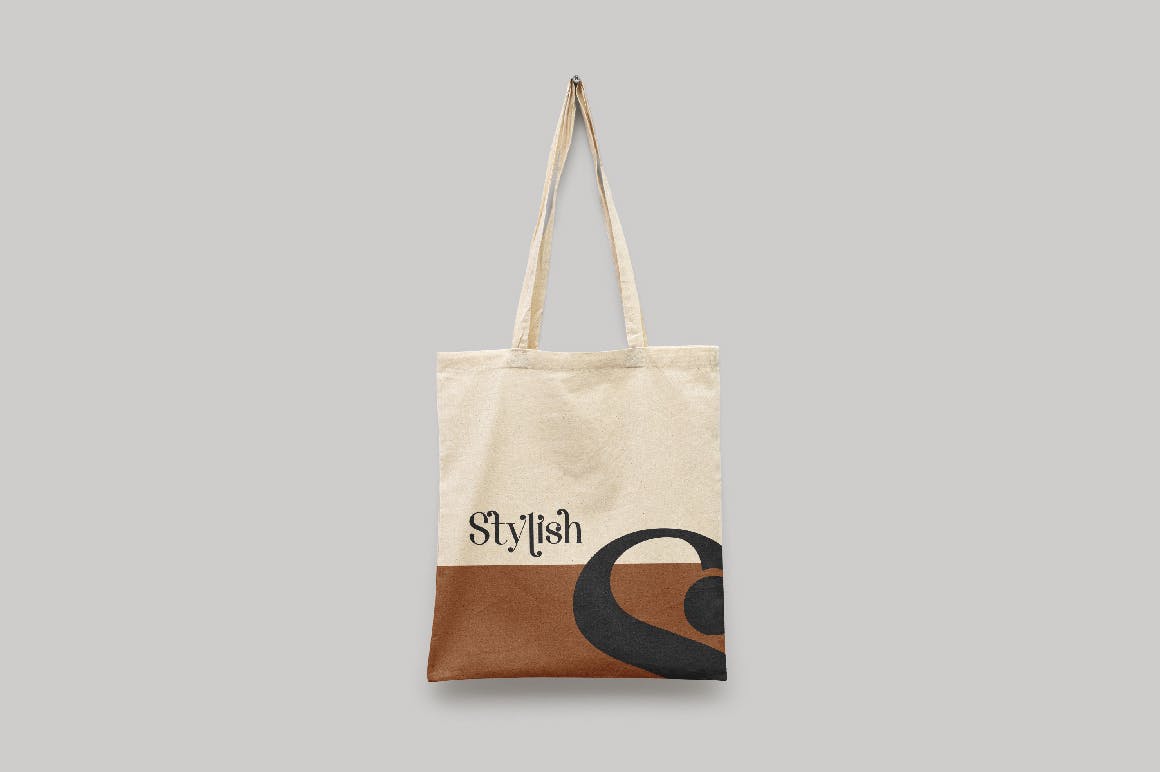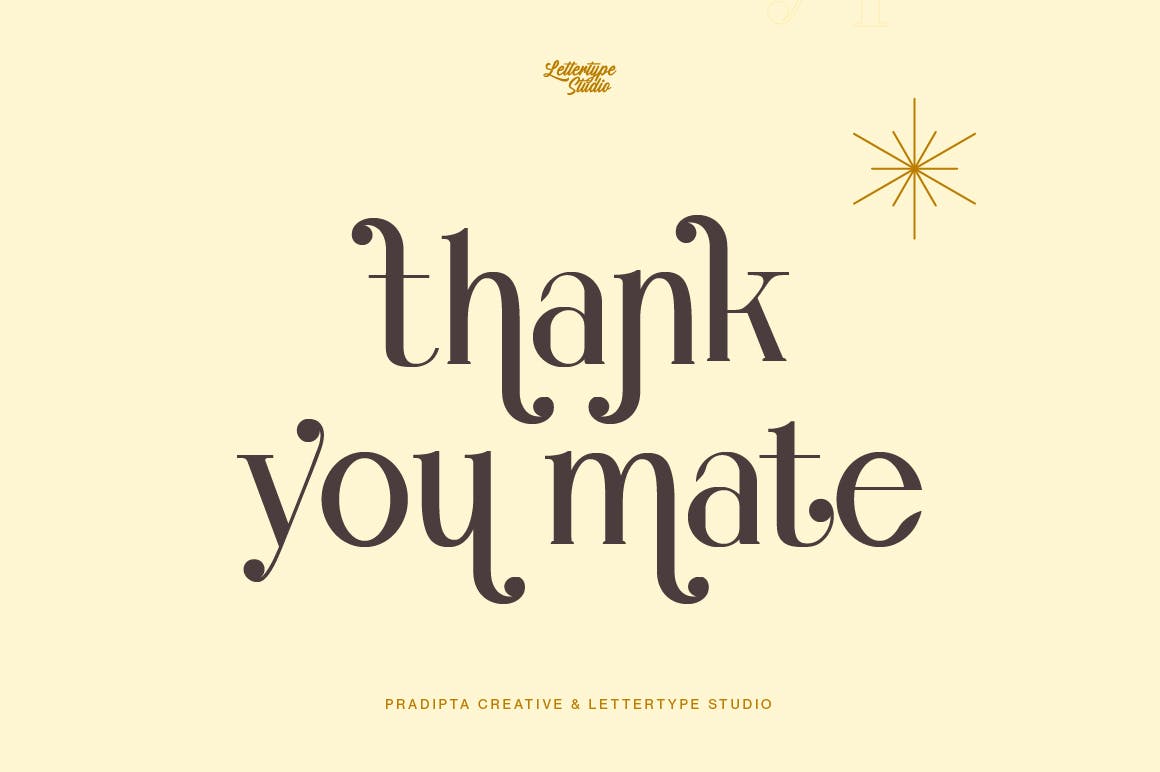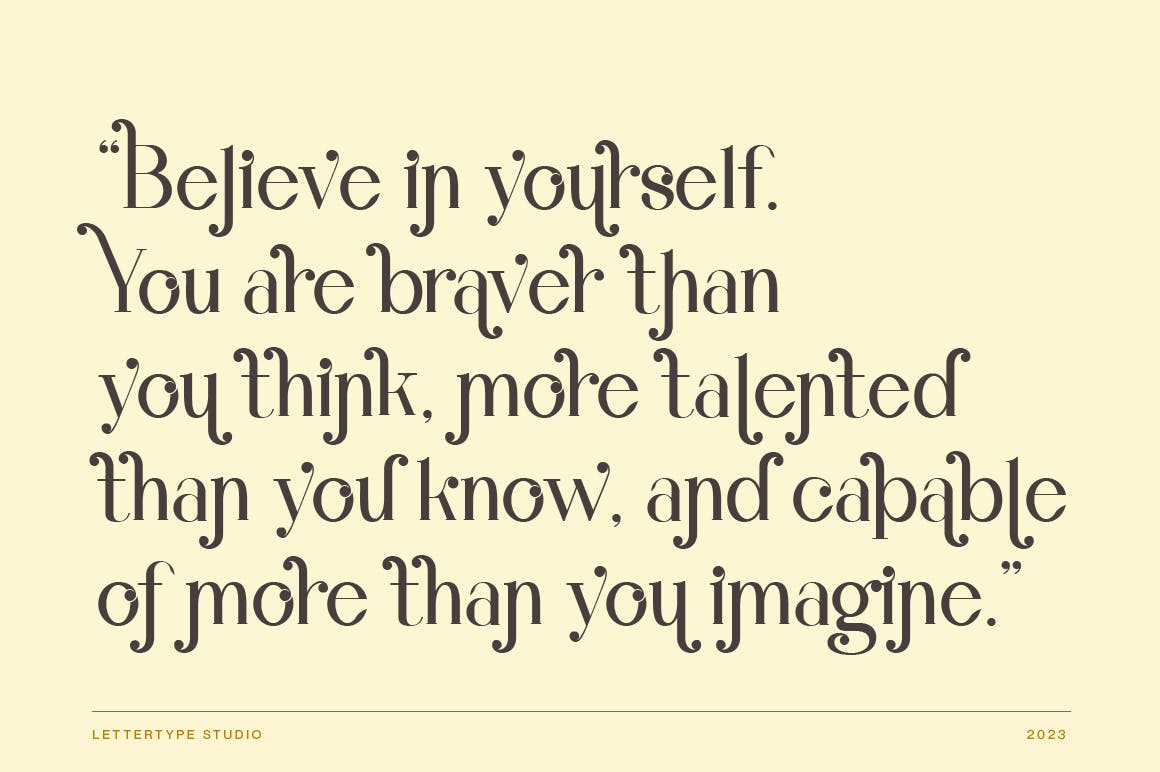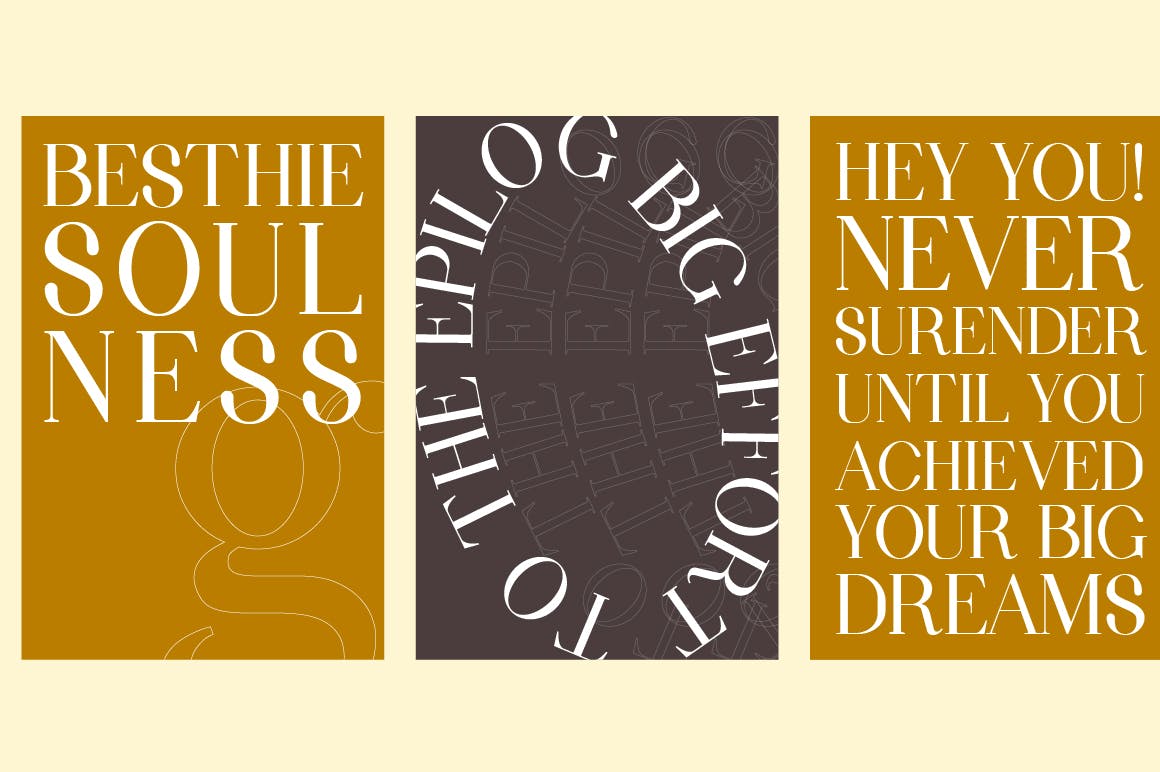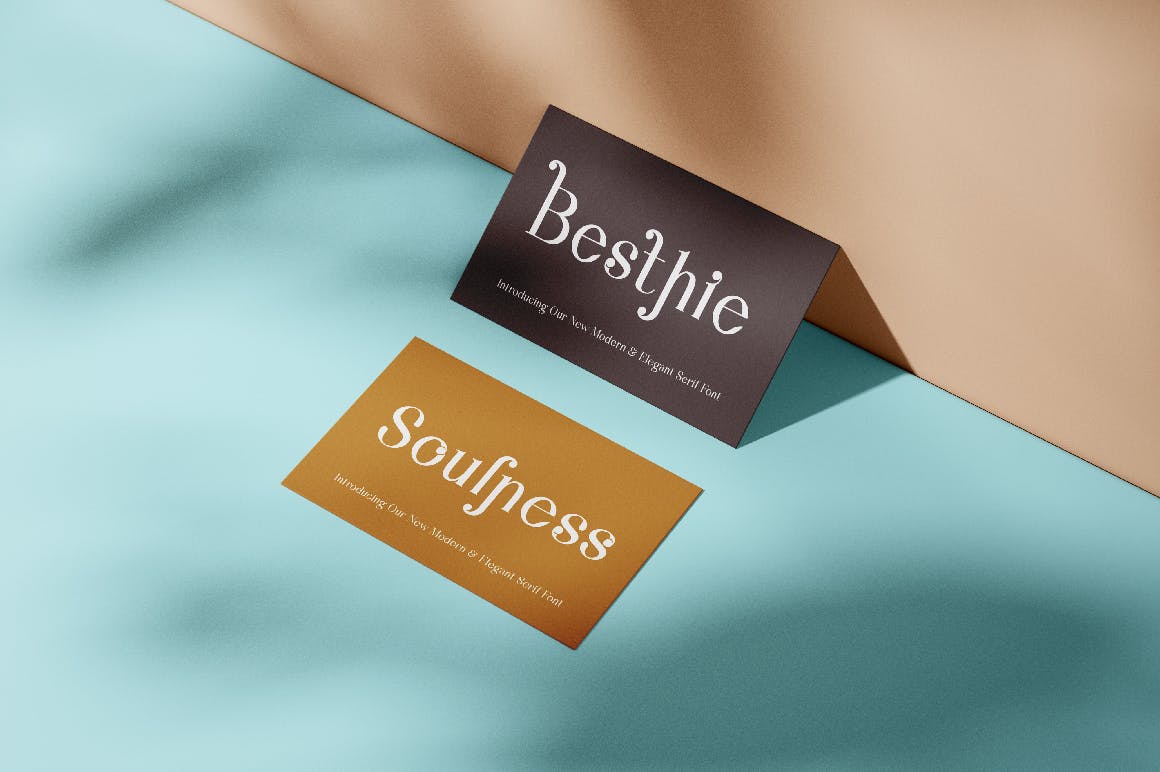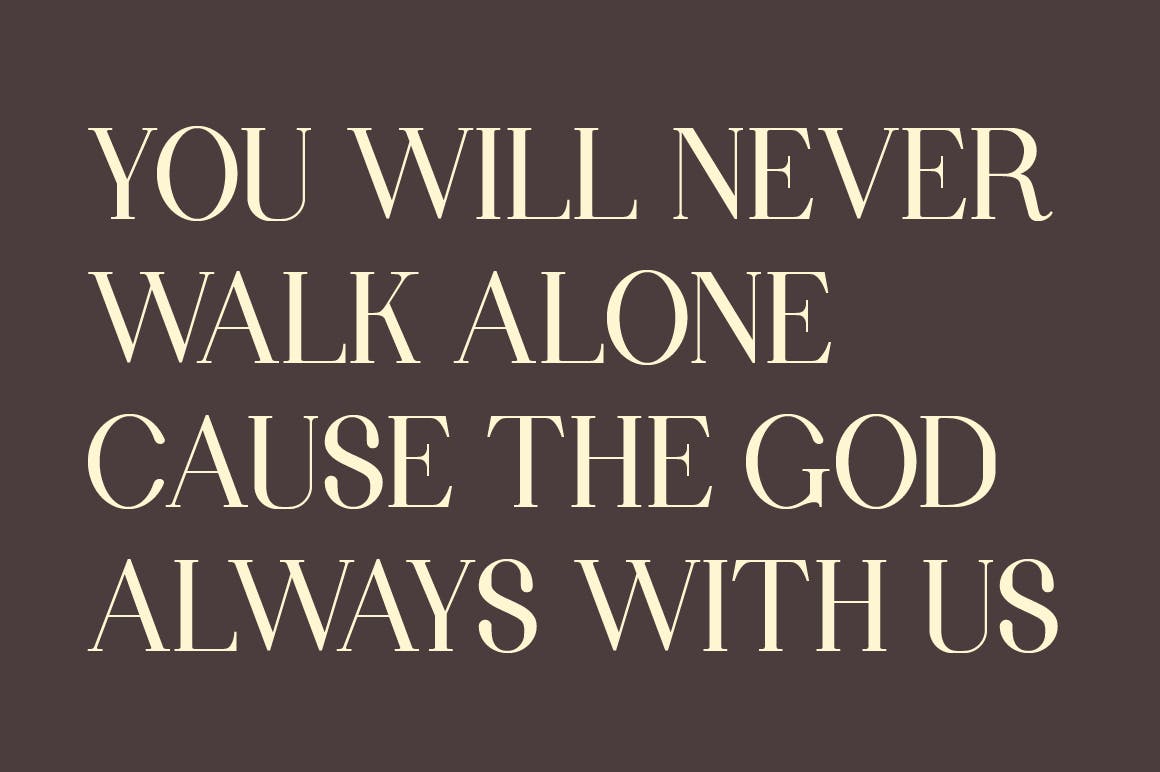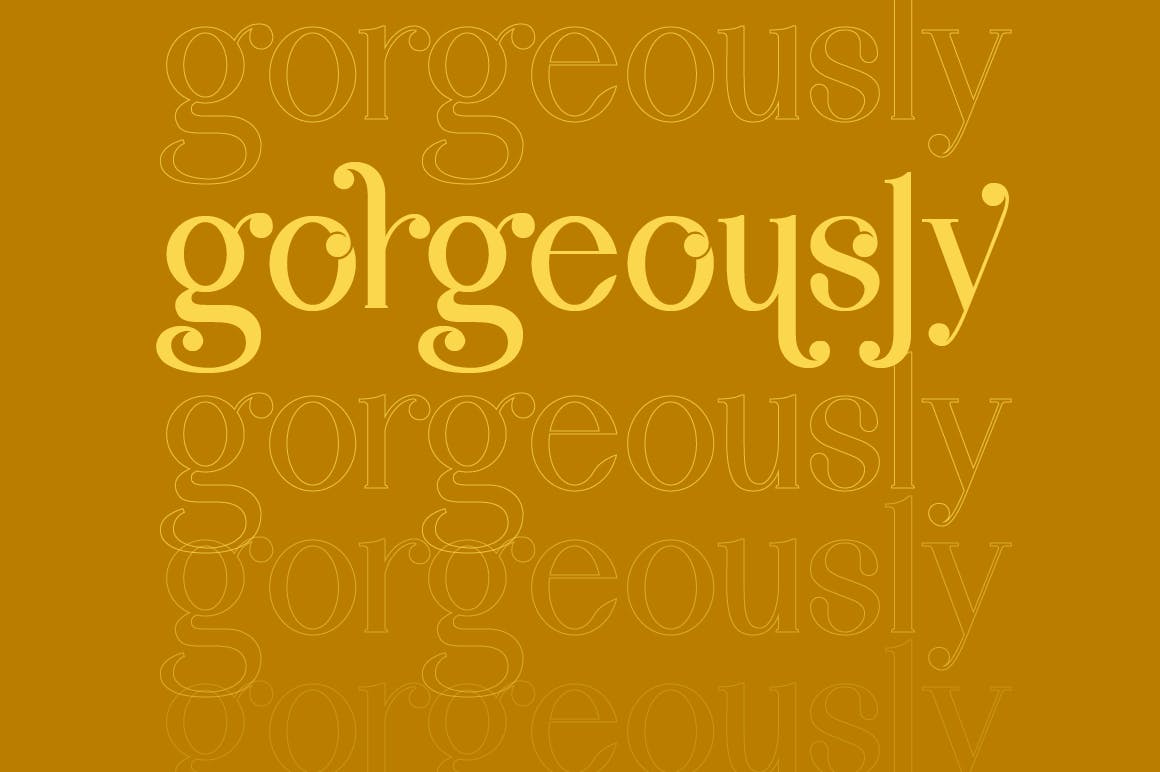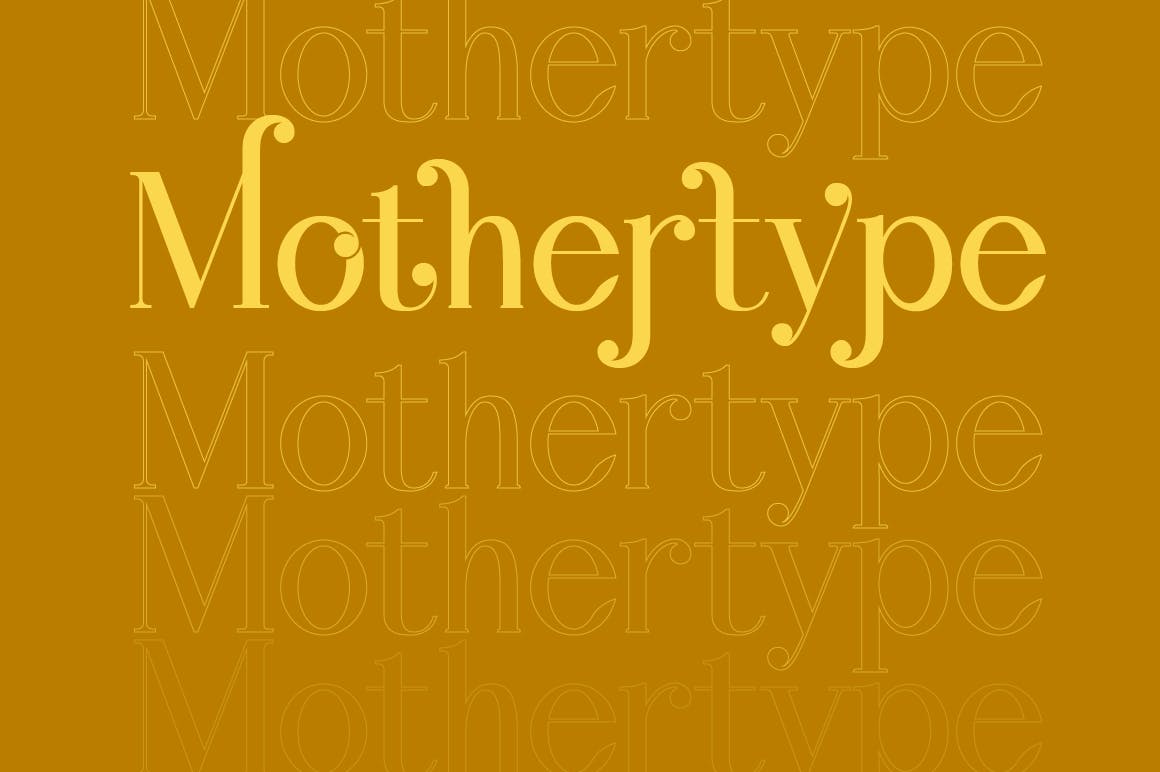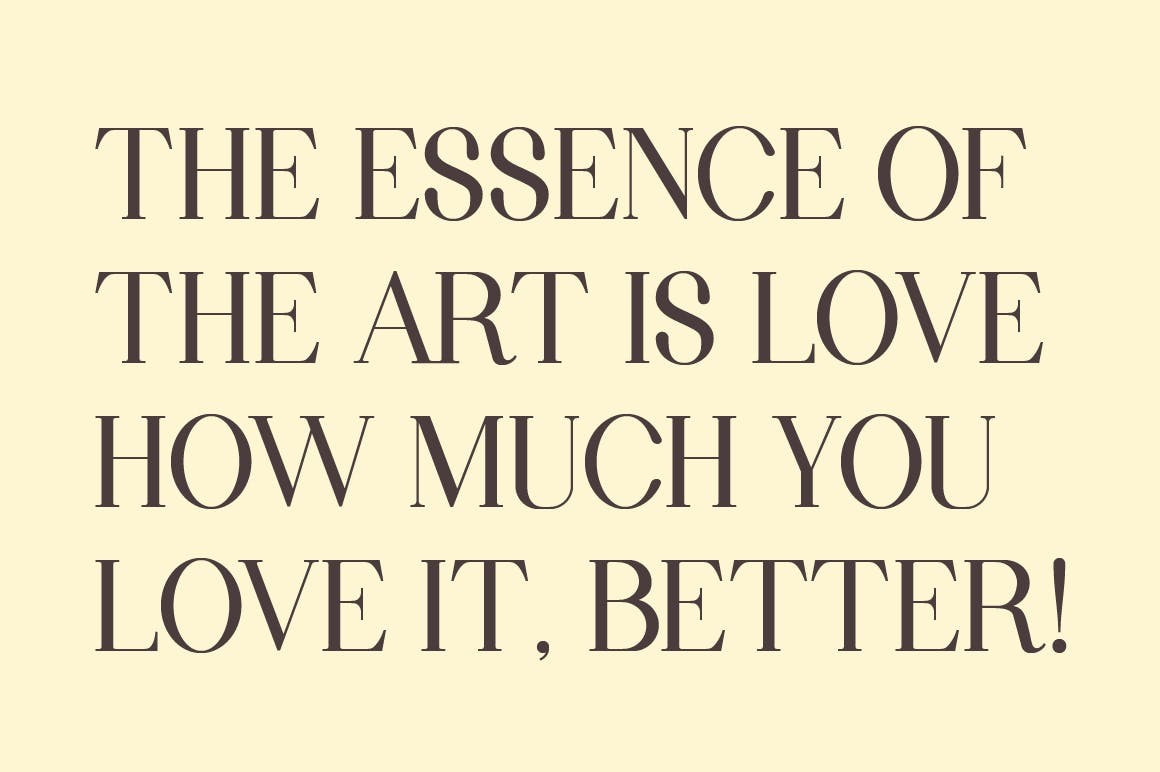
Besthie Soulness یک فونت سریفی لوکس، کلاسیک و مدرن است که با مجموعهای از استایلهای جذاب طراحی شده است.
این فونت برای طراحی لوگو، برندینگ، تابلوها، پوسترها، دعوتنامههای عروسی، محصولات آرایشی یا مد و موارد دیگر بسیار مناسب است!
فونت Besthie Soulness به پروژه یا برند شما ظاهری لوکس، کلاسیک و مدرن خواهد بخشید.